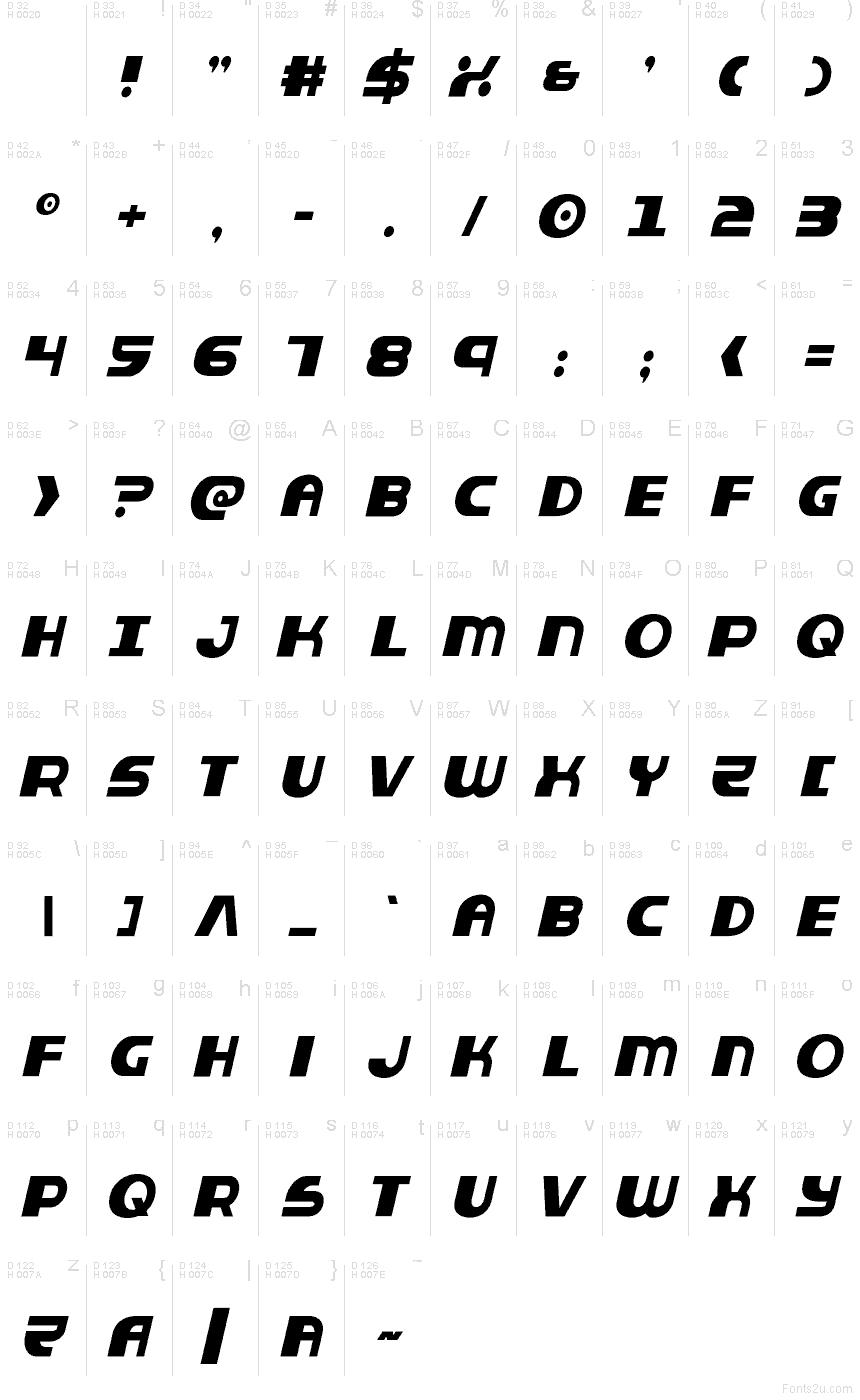
Dashiel Condensed Italic de Iconian Fonts es una tipografía display gratuita de ciencia ficción con una inclinación intensa y curvas recortadas que parecen sacadas de logotipos retrofuturistas. Las letras son anchas pero están agrupadas de forma compacta, con terminaciones diagonales contundentes y muescas internas suaves que le dan a la tipografía un ritmo rápido y técnico, en lugar de un acabado neutro y plano.
Funciona de maravilla en branding de juegos, portadas de cómics, titulares de carteles, tarjetas de título y envases de estética tecnológica donde las palabras cortas necesitan más movimiento que pulido. Como tipografía gratuita, resulta especialmente natural para bocetos de logotipos, gráficos para streamers, diseños de tipo insignia y titulares compactos, ya que las mayúsculas encajan formando una silueta densa y con inclinación hacia adelante.